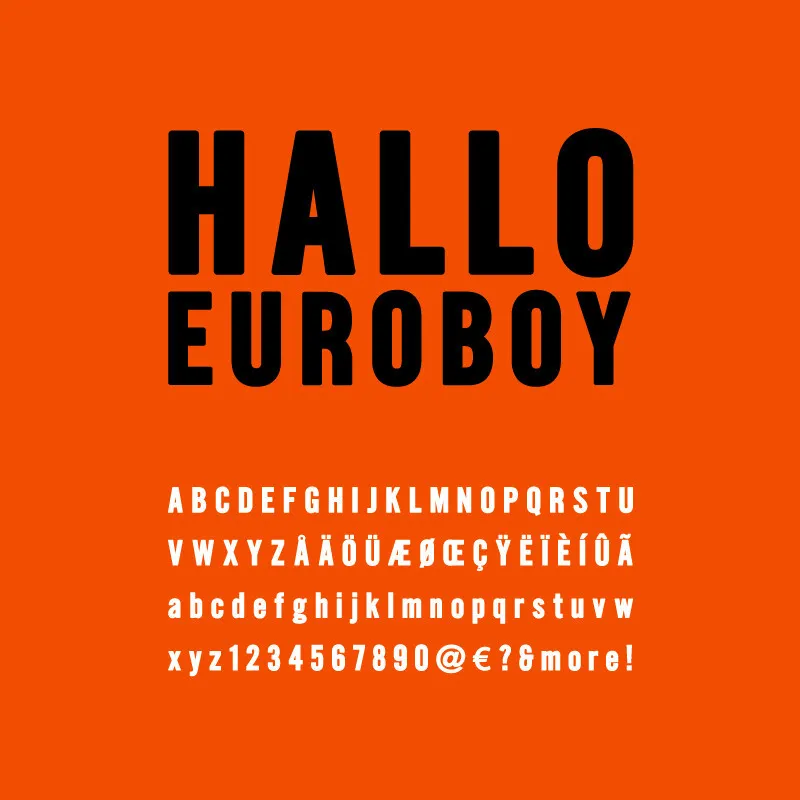
A fonte ‘Hallo Euroboy’ é uma tipografia gótica bold com toques suaves, perfeita para headlines em outdoors ou sinais de segurança no local de construção. Inspirada no esquecido alternativo gothic de Morris Fuller Benton (o original que veio muito antes do Trade Gothic), esta fonte combina a severidade característica da tipografia gótica com um toque mais suave, tornando-a ideal para destaque em anúncios e sinais importantes. Suas linhas estilizadas criam uma aparência elegante e forte, adequada tanto para ambientes comerciais quanto públicos. Uma fonte inspiradora para designers que desejem um equilíbrio entre severidade e suavidade na sua próxima criação visual.